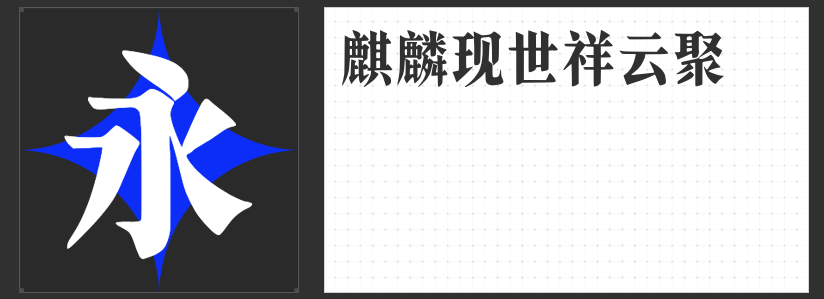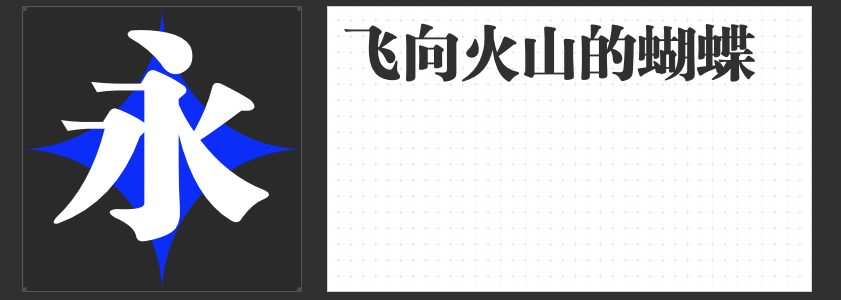
四款宋体新韵:传统与现代交织的视觉美学
宋体作为汉字设计的经典范式,始终在传统与现代的碰撞中焕发新生。今天推荐四款风格各异的商用宋体字体,它们以独特的笔触与结构,为设计注入兼具文化底蕴与时代张力的视觉语言。
1. 励字大标宋简繁
这款字体以“横轻竖重”为骨架,横线尾与直线头的三角状装饰如刀刻斧凿,既保留老宋体的古朴韵味,又融入黑体的现代力量感。点、撇、捺、钩的尖端笔触如剑锋出鞘,字形端正清秀却不失刚劲,适合文化出版、品牌标题等场景,传递稳重而不失灵动的气质。其“老宋体与黑体结合”的特性,让传统与现代在设计中无缝对话。
2. 高手兵克高雅宋
以“窄长字形”为视觉符号,这款宋体如一位身姿挺拔的舞者,在有限空间中延展出无限优雅。笔画纤细却富有韧性,衬线装饰如裙摆轻扬,既保留宋体的端庄,又以修长比例赋予设计轻盈感。适用于高端时尚、艺术展览等场景,其优雅气质能瞬间提升版面的格调,让文字成为视觉焦点。
3. 机甲宋麒麟号
当宋体遇见机甲,这款字体以“修长机甲身,柔美宋体魂”颠覆传统认知。笔画融合书法规范与机械美学,横竖转折处如金属铠甲般硬朗,而点、捺的弧度又暗藏宋体的柔美韵律。其强烈的视觉冲击力,适合科技产品宣传、未来感海报等场景,为设计注入硬核浪漫,让文字成为科技与人文的桥梁。
4. 励字新粗宋简
在传统宋体“横细竖粗”的基础上,这款字体以“扁方字形”打破常规,横向延展的笔画如大地般沉稳,竖向笔画的粗重则如山岳般坚实。衬线装饰简洁有力,尖端笔触锐利如刃,既保留宋体的辨识度,又以创新结构赋予设计现代感。适用于广告标题、包装设计等场景,其独特形态能瞬间抓住观者目光。
这四款字体以不同维度诠释宋体的可能性:它们或承袭传统,或颠覆常规,或融合科技,但始终以“端正”为根基,以“变化”为灵魂,为设计注入跨越时空的视觉魅力。选择一款与项目调性契合的宋体,或许正是让文字从“工具”升华为“艺术”的关键。